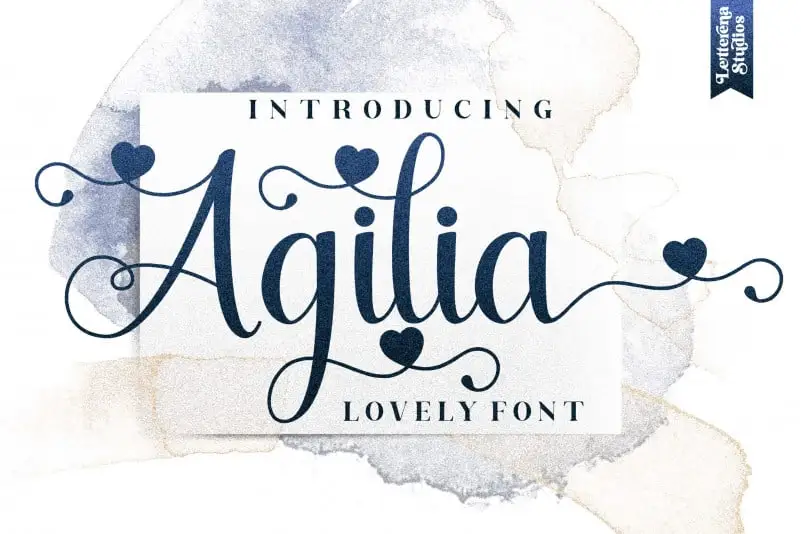
A Agilia Calligraphy Font é uma fonte elegante e delicada, projetada para transmitir um toque fresco e suave através de escrita a mão. Seu estilo clean, denso fino e perfeitamente liso proporciona um toque sofisticado às criações digitais que você desejar adicionar à sua próxima peça de design. Além disso, o facto de ser PUA encoded torna-a ainda mais versátil, permitindo a fácil utilização de todos os símbolos e swashes. Esta font é uma ótima opção para designers que procuram um touch único em suas criações gráficas, proporcionando aos designs um toque distintivo e sofisticado.